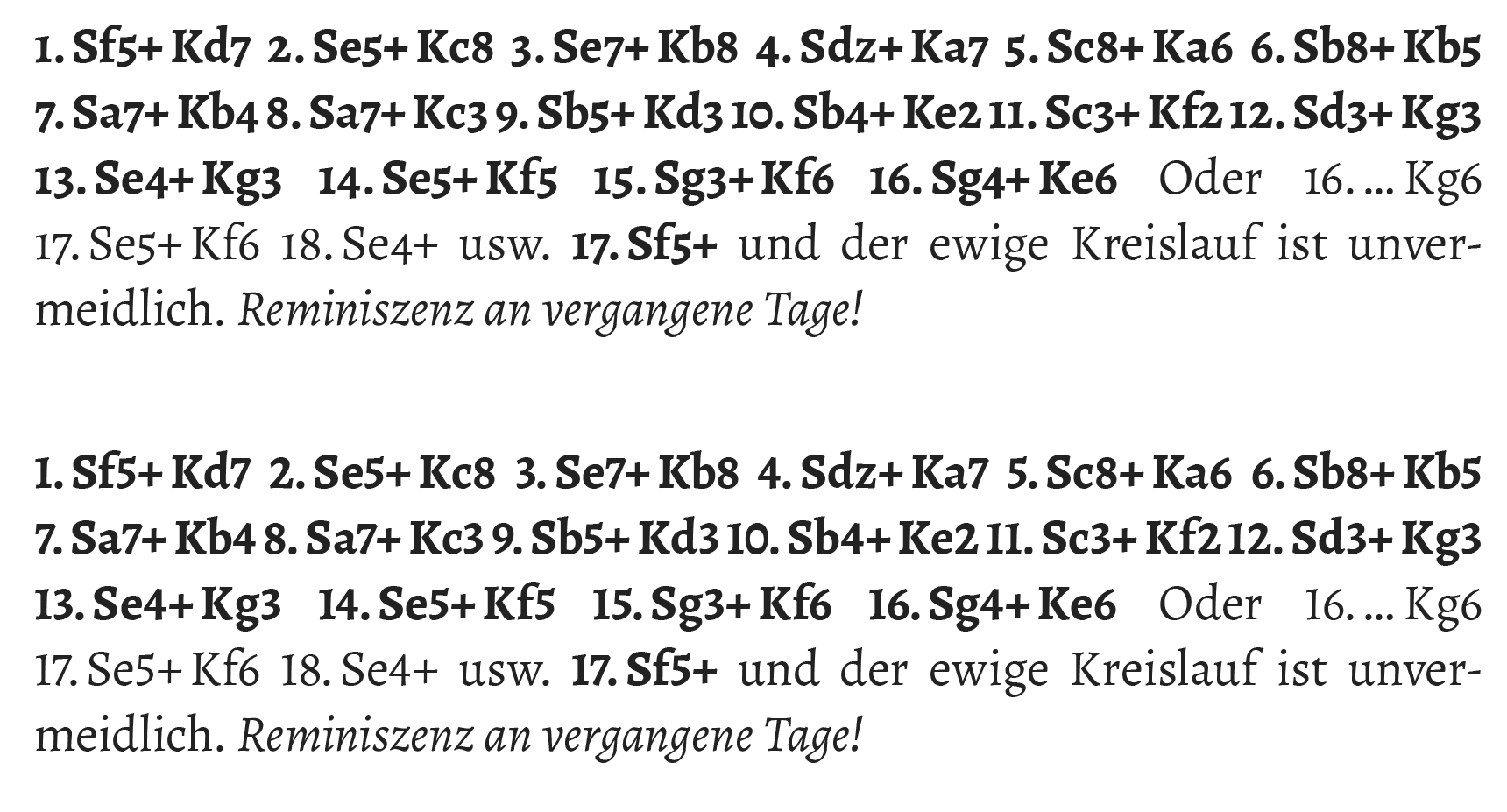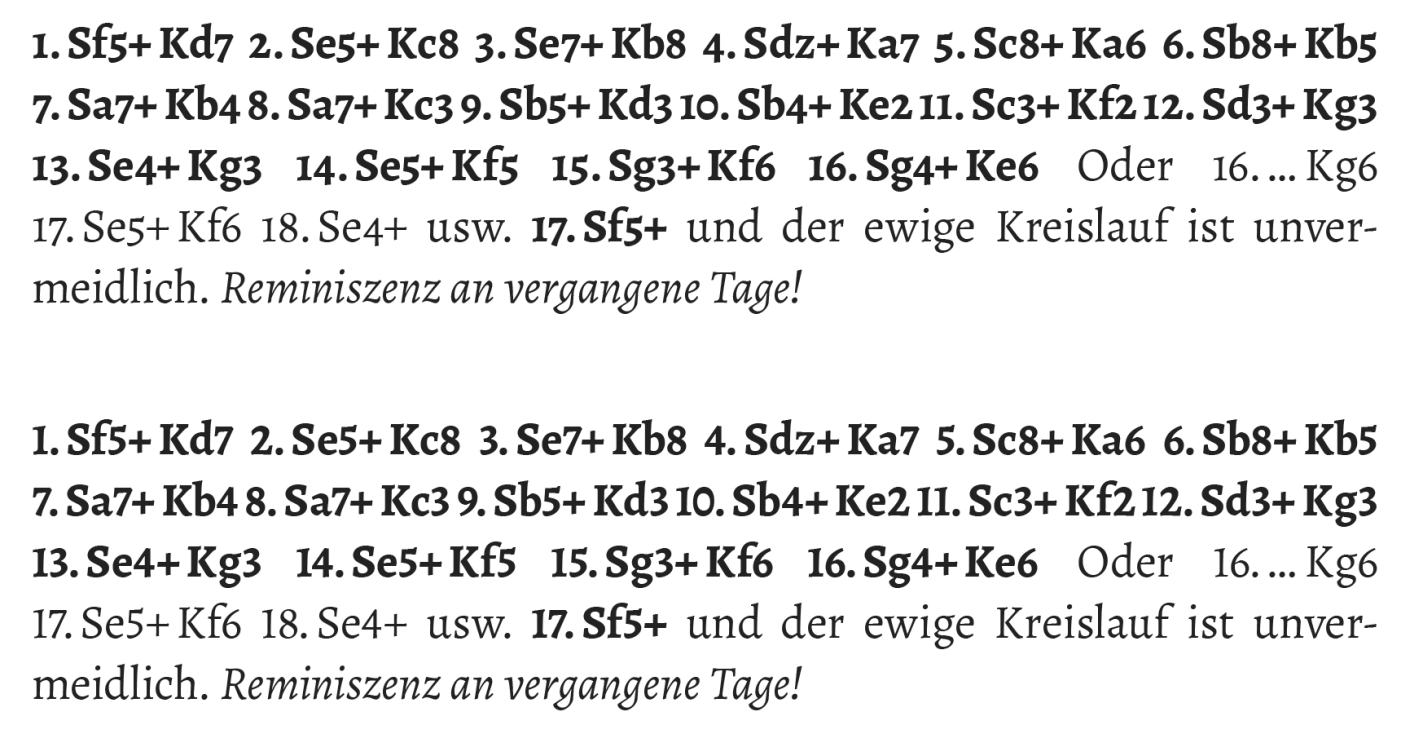
Wie ist richtige Angabe von Schachzügen?
Ich habe hier ein Sachbuch beim dem ich nicht Recht weiterkomme.
In dem Buch geht es um Schach. Es werden einige Partien erklärt und dabei Züge angegeben.
So z. B. „5.e3“ oder auch „1.e4 e5 2.Sf3 d6“. Das norwegische Original ist mir keine Hilfe. Zwischenräume sind wild verteilt. Genauso sieht es in den Schachforen aus. Immer viele Varianten in der gleichen Zeile.
Im Moment habe ich mich für die Variante entschlossen, hinter dem Punkt der Zugnummer ein Achtelgeviert einzufügen. Ansonsten geschützte Leerzeichen und auch kein Komma zwischen den Zügen.
Gibt es eine Regel.
Eine entsprechende Regel fällt mir nicht ein, habe allerdings noch nie ein Schachbuch gesetzt. Ich habe eben mal in meinen Schachbüchern geschaut, bei allen kommt der Zug direkt nach dem Punkt, der Zug von schwarz wird mit einem normalen Leerschritt abgetrennt. Soll nur der zweite Zug angezeigt werden, also quasi eine Fortsetzung der Zugreihenfolge nach einem erklärenden Text, kommen zwei Punkte, also etwa so:
11.Te3
Der Turm lorem ipsum usw.
11...La4
Ganz ehrlich, ich muss sagen das sieht überhaupt nicht komisch oder gar falsch aus für mich, das ist, je nach Schrift usw. gut lesbar und nachvollziehbar.
Im Original oder auch in Foren sind oft Leerzeichen.
wie „5. e3¡
Aber ich habe auch Eröffnungszug „1…d6“. Das ist also eine Zugreihenfolge.
Dann hat aber auch „1.d4“ Sinn. Also besser ohne Zwischenraum.
Scheint mir so logischer.
Naja, ich würde es auf jeden Fall klären bzw. ausprobieren, generell kommt ja immer mal eine ganze Abfolge von Zügen, da stehen dann z.B. 10 oder noch mehr Züge hintereinander weg, so eine Folge würde ich mal mit wie auch immer gearteten Zwischenraum und ohne überprüfen bzw. anbieten.
Die Zugnummer, also »1.«, »2.« usw., bezieht sich ja auf den gesamten jeweiligen Zug. Nachdem nun die beiden Teilzüge von Weiß und Schwarz durch ein ganzes Leerzeichen getrennt sind, entsteht der Eindruck, dass die Zugnummer nur zum weißen Teilzug gehört, wenn man da nicht auch mindestens ein ganzes Leerzeichen dazwischensetzt.
Dieter bietet ja jetzt die andere Variante mit Leerzeichen an.
Obwohl ich bei „1.e4 e5 2.Sf3 d6“ schon sehen kann was zusammen gehört.
Varianten anbieten muss ich so nicht. Der Lektor hat es mir überlassen.
Obwohl ich bei „1.e4 e5 2.Sf3 d6“ schon sehen kann was zusammen gehört.
Varianten anbieten muss ich so nicht. Der Lektor hat es mir überlassen.
Dann würde ich mich für ebendiese entscheiden.
Ich lese ja nun kaum Schachliteratur, aber auf die Schnelle stört mich hier zumindest theoretisch, dass Ziffern auf engstem Raum für verschiedene Sachen stehen: einmal die Zugnummer und dann die Beschreibung des Zugs an sich. Und ich frage mich, ob es vielleicht was bringen könnte, diese beiden Rollen typografisch zu unterscheiden.
1. Idee: Farbige Unterscheidung. Die Zugnummern grau oder in einer nicht zu aufdringlichen Farbe.
2. Idee: Kapitälchenziffern¹ für die Zugnummern, Versalziffern für den Rest.
Unsinn oder einen Versuch wert? :-?
1. Also keine Mediävalziffern (0123456789), sondern solche, bei denen alle Kapitälchenhöhe haben und auf der Grundlinie sitzen.
Komplett ohne Leerraum finde ich komisch. Mir ist bis jetzt meistens die Notation 3. Lf4 g5 bzw. 3. Lf4 Blablabla. 3… g5 blubb, also mit Leerzeichen nach Punkt und Ellipse untergekommen. Typografisch liegt die Wahrheit vielleicht zwischen kein Abstand und vollem Leerzeichen.
Ich kann aber überhaupt nicht gut Schach spielen. Hatte aber die letzte WM mitverfolgt.
Edit: Wie hier beschrieben:
https://en.wikipedia.org/wiki/Algebraic_notation_(chess)#Notation_for_a_series_of_moves
Bei Wikipedia steht immer ein Leerzeichen nach der Zugnummer, was mich freut, weil es meine Sicht der Dinge bestätigt. Bei Wikipedia war als Zeichen, dass eine Figur geschlagen wird, ein kleines x gesetzt. Ich meine aber, das das Malzeichen × richtig wäre, und habe das deshalb entsprechend geändert.
Ich habe mal Beispiele angehängt, 4 und 5 ist wunderbar, ich finde das übersichtlich genug. Also ich bleibe mal bei meiner Meinung, ich würde direkt hinter dem Punkt weiter setzen, gerade bei Blocksatz. Hier jetzt noch mit unterschiedlichen Zwischenräumen zu arbeiten bedeutet sehr viel Mehraufwand, zumal wenn die Partien so im Manuskript geliefert wurden. Gerade bei engeren Zeilen im Blocksatz habe ich so eine bessere Gliederung zwischen den verschiedenen Zügen.
Ich hoffe es ist erlaubt die Bilder anzuhängen oder widerspricht das Copyrightrichtlinien?
Ich habe mal Beispiele angehängt, 4 und 5 ist wunderbar, ich finde das übersichtlich genug. […] Gerade bei engeren Zeilen im Blocksatz habe ich so eine bessere Gliederung zwischen den verschiedenen Zügen.
Nehmen wir Beispiel 5: Ich sehe »1.Sf8+« als Block, dann einen zweiten Block »Kd7«, dann einen dritten Block »2.Se5+«, dann einen vierten Block »Kc8«, dann einen fünften Block »3.Se7+«, dann einen sechsten Block «Kb8« und so weiter. Der erste Block beinhaltet eine Nummerierung (die für den ersten Zug steht), der zweite Block hat keine Nummerierung, obwohl er mit zum ersten Zug gehört, und so geht es weiter. Mit Logik oder mit klarer Zuordnung hat das nichts zu tun.
So werde ich es wohl machen. Eine Regel scheint es so richtig nicht zu geben, die Muster zeigen das auch. Bisher habe ich auch nur einzelne Züge im Text verteilt. Das wird sich wohl ändern wenn Magnus in die zweite WM kommt.
Wie immer Einheitlichkeit sollte Wichtig sein. Mediävalziffern sind vom Verlag sowieso vorgegeben.
Sollte jemand geschlagen werden natürlich ein Kreuz, kein X. Das ist klar.